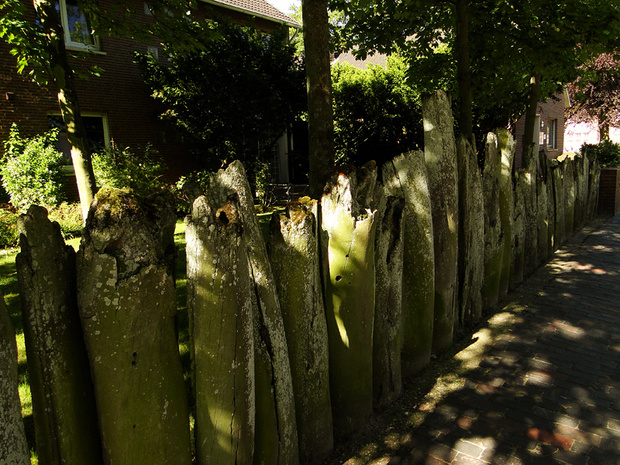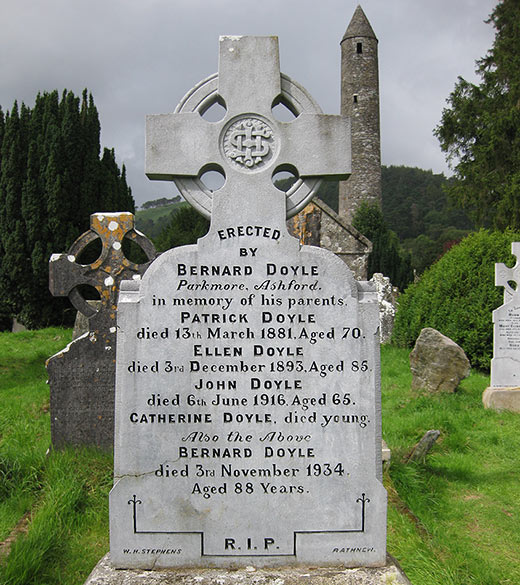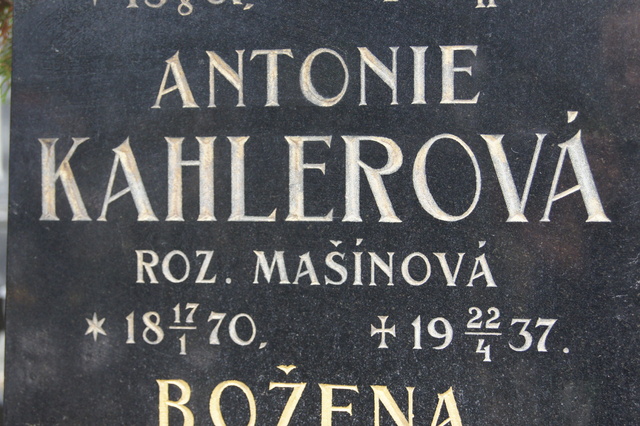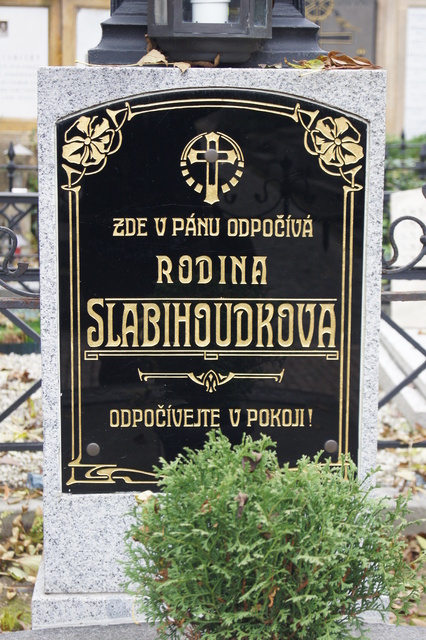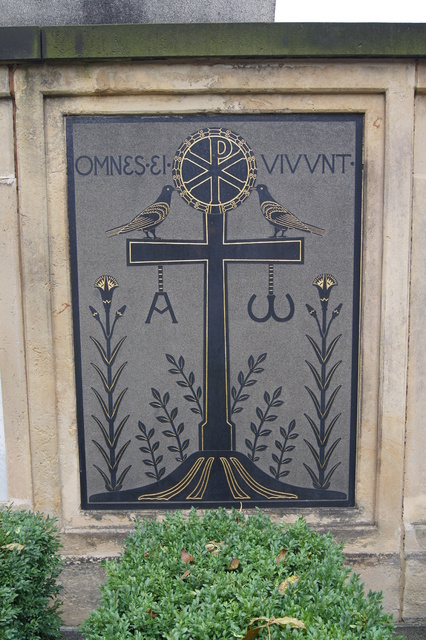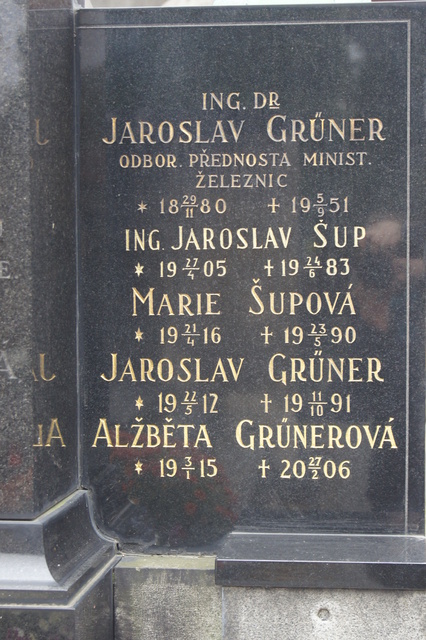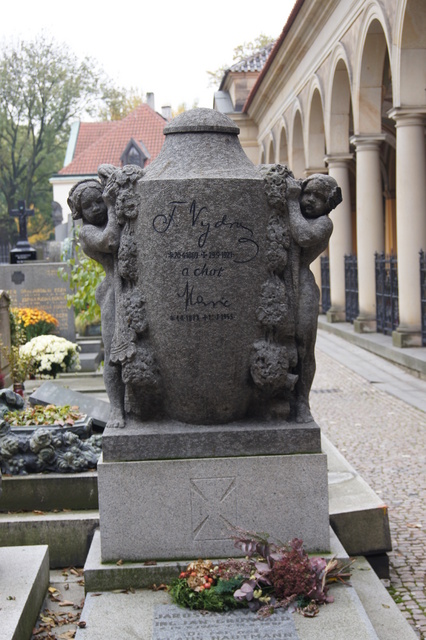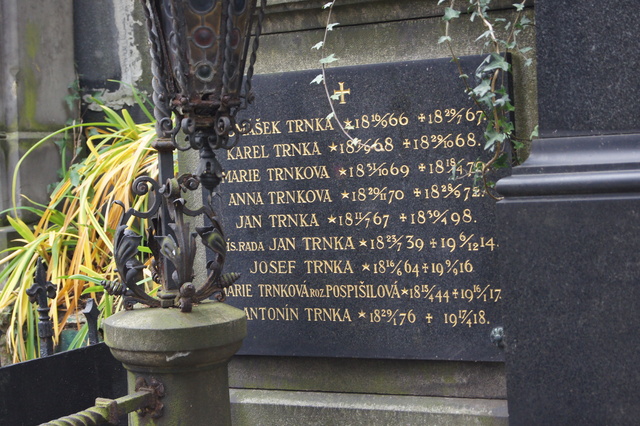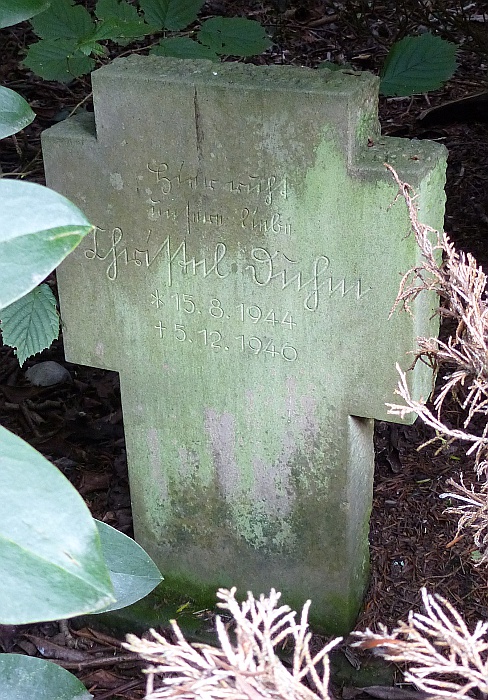
Tombstone-Spotter
… also diese ... naja, schiefen steine die keine steine sind.
das könnten Walknochen sein, die hab ich schon auf Rømø gesehen :-)
jep, auf Rømø haben sie auch einen schönen Zaun gebaut:
grabsteine auf dem 'piratenfriedhof' borkum [...]
Aaaaarrrr! Danke, Sprotte :piratensmiley: ;-)
Neulich war ich sehr angetan von den Mustergräbern auf der Buga 2011 in Koblenz. Hier stellen Steinmetze und Gärtner 120 Mustergräber in einem kleinen Friedhof vor. Leider habe ich nicht fotografiert und im Netz findet man nur die langweiligen Exemplare.
Der Trend scheint zu schmalen Säulen und sehr dezenter Beschriftung zu gehen. Einige Säulen waren um die Ecke oder gar umlaufend beschriften. Am meisten beindruckt haben mich helle Natursteinplatten, die an einer Eichenholzwand hingen. Die Beschriftung erfolgte mit "aufgesetzten" Buchstaben an den rauhen Kanten der Steinplatten, also fast nicht lesbar.
Sehr schön war auch die Beschriftung des T-Shirts einer Fotografin, die wohl den ganzen Tag da herum steht:
Ja,
ich muss hier stehen.
Nein,
hier liegt niemand.
Ja,
ich muss hier stehen.
Nein,
hier liegt niemand.
:mrgreen:
Stein und Metall sind eh tolle Medien für Schriften und Logos :biglove: Das Augenmerk dieses Videos liegt eigentlich auf der Videowand, aber der heimliche Star ist das Logo bei etwa 00:10 :-D
Hallo zusammen, das ist ein schöner Thread! In Irland gibt es jede Menge Grabsteine mit kunstvoller Beschriftung. Hier ein interessantes Beispiel mit Eurostile. Sieht so aus, als wäre die Beschriftung in eine Betonplatte geprägt?
Das Thema ist zu schön, daher noch weitere Grabsteine aus Irland.
Hallo ich möchte mich mit einigen Bildern aus Prag wieder zurückmelden.
Die Art wie hier das Datum geschrieben wird fand ich besonders spannend.
Ein paar Fundstücke vom Vareler Friedhof:
Ligaturen und freie Bitte-hier-Datum-einmeißeln-Felder aus dem 17. Jhdt.:
Ich habe mal mein Archiv von Type-Design-Vorlagen durchsucht, und dieses Bild gefunden, dass mir ein guter Bekannter (H.-G. Barthoff aus Heringsdorf) zur Verfügung gestellt hat:
Das erste Bild sieht so aus, als ob er mit seinem Mercer voll in eine Kirche gekesselt wäre...
Ja. Autos scheinen überhaupt eine große Rolle zu spielen! Und einer sitzt auch noch am Tisch und pichelt ... Seltsame Sitten gibt es!
Das erste Bild sieht so aus, als ob er mit seinem Mercer voll in eine Kirche gekesselt wäre...
Ist es schon wieder soweit, daß deutsche Panzer in russische Kirchen fahren? Aber immerhin, außer, daß die Krawatte etwas derangiert ist, scheint ihm nichts weiter zugestoßen zu sein. Deutsche Wertarbeit eben. Überhaupt sind das weit überwiegend deutsche Karossen auf den russischen Gräbern.